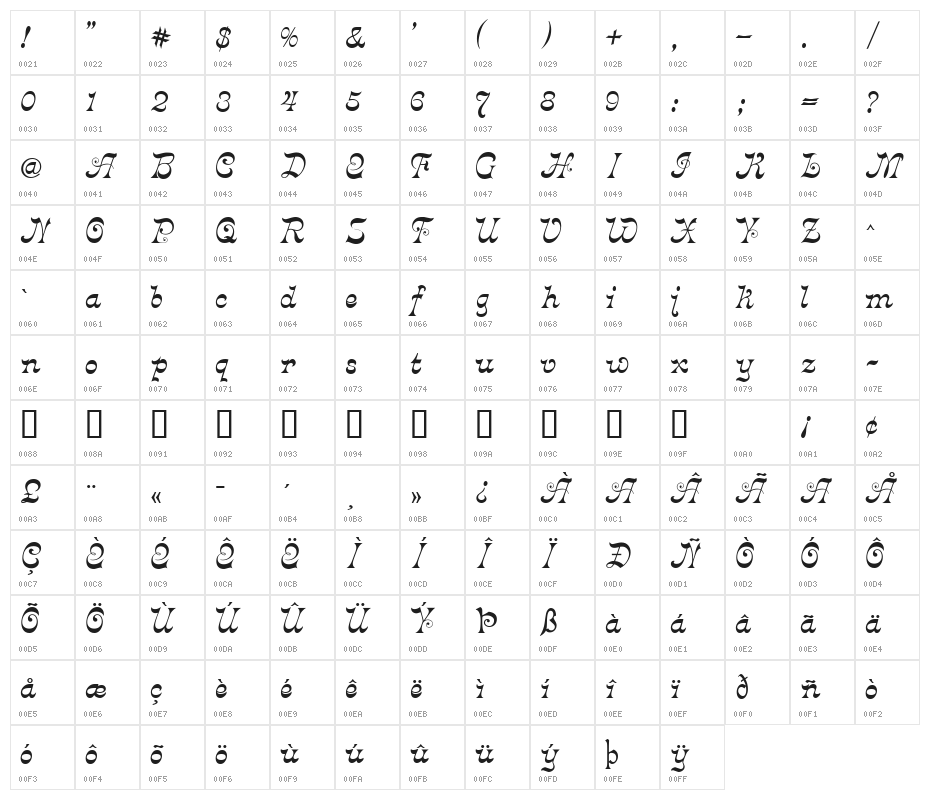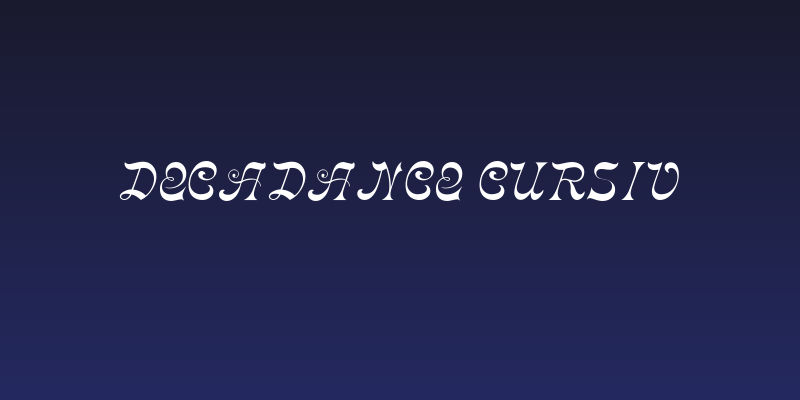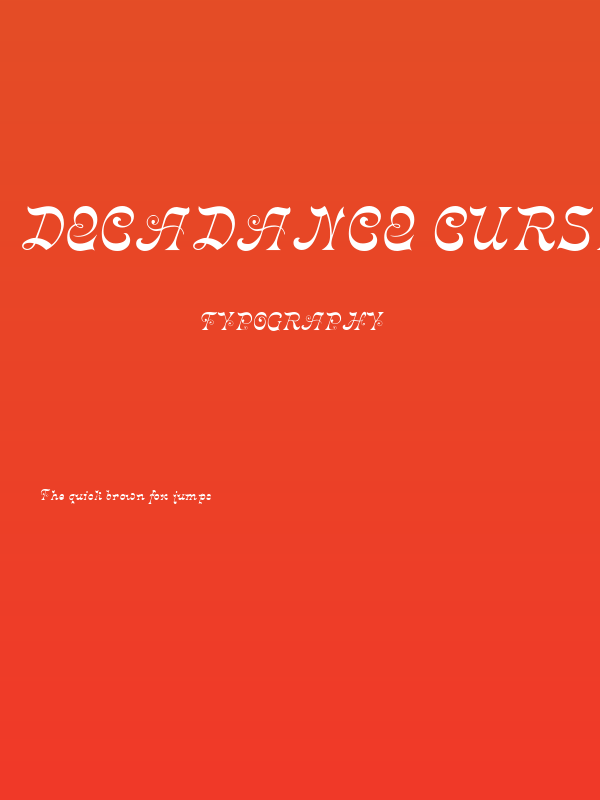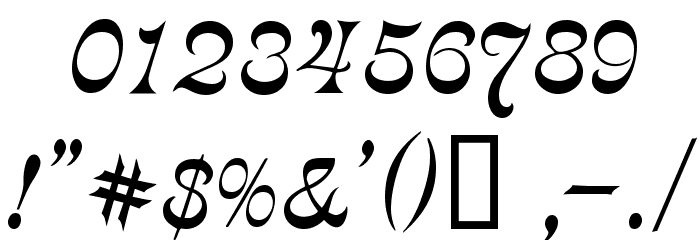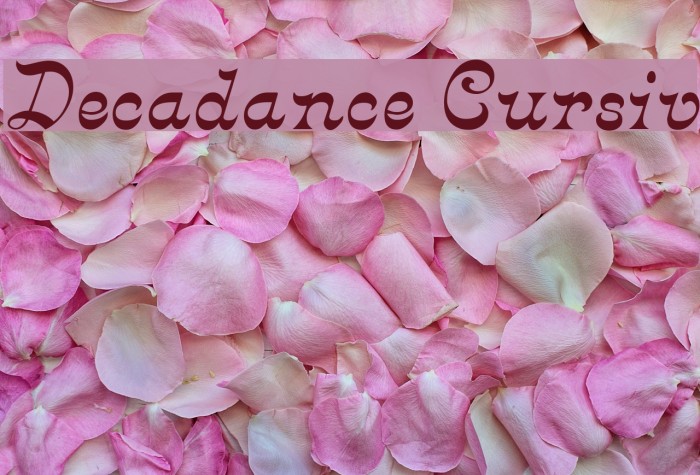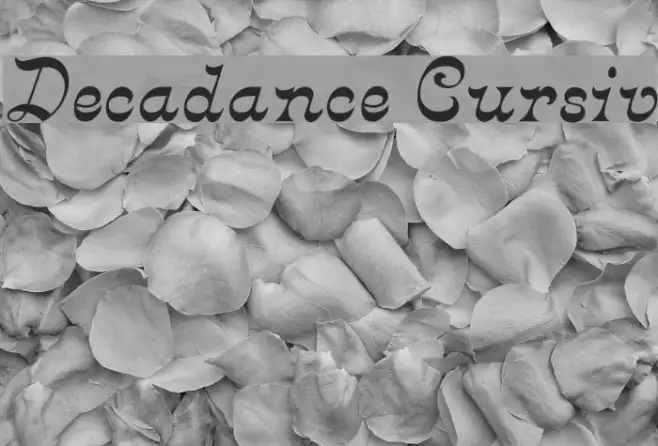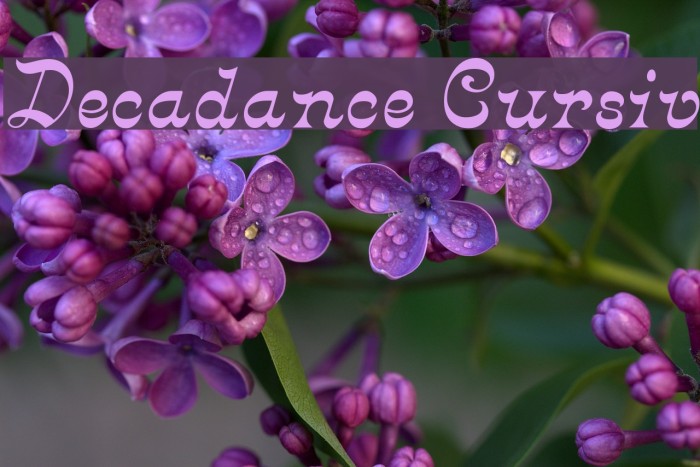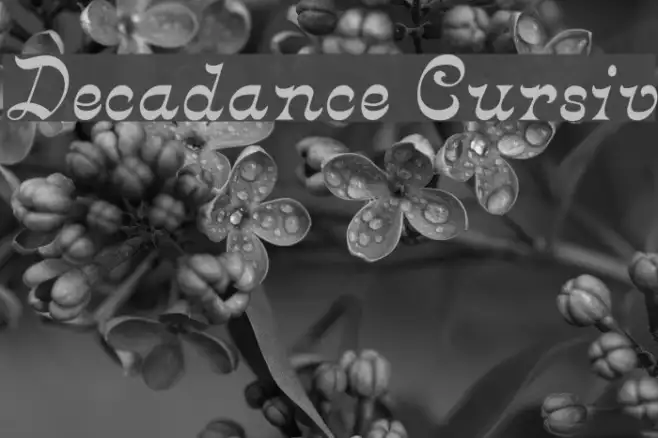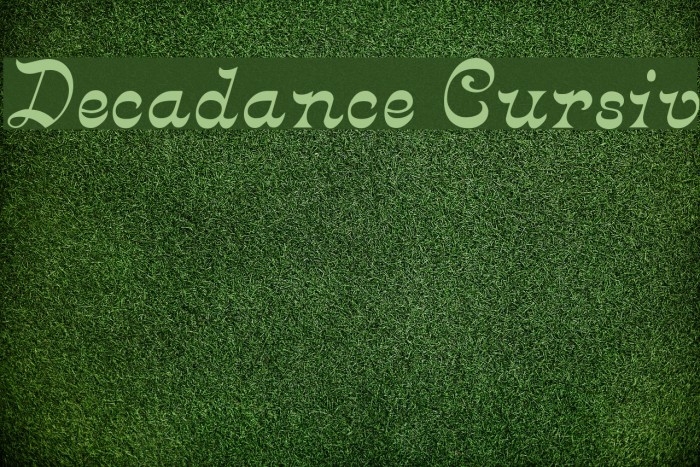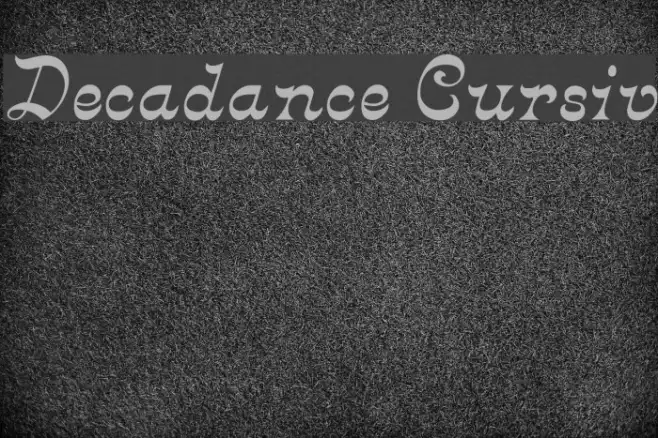
Decadance Cursiv Font
| Cas d'utilisation | Logos, Invitations, Artistic Projects |
| Projets proposés | Ideal for wedding invitations, greeting cards, artistic posters, and branding materials that require a touch of elegance and creativity. |